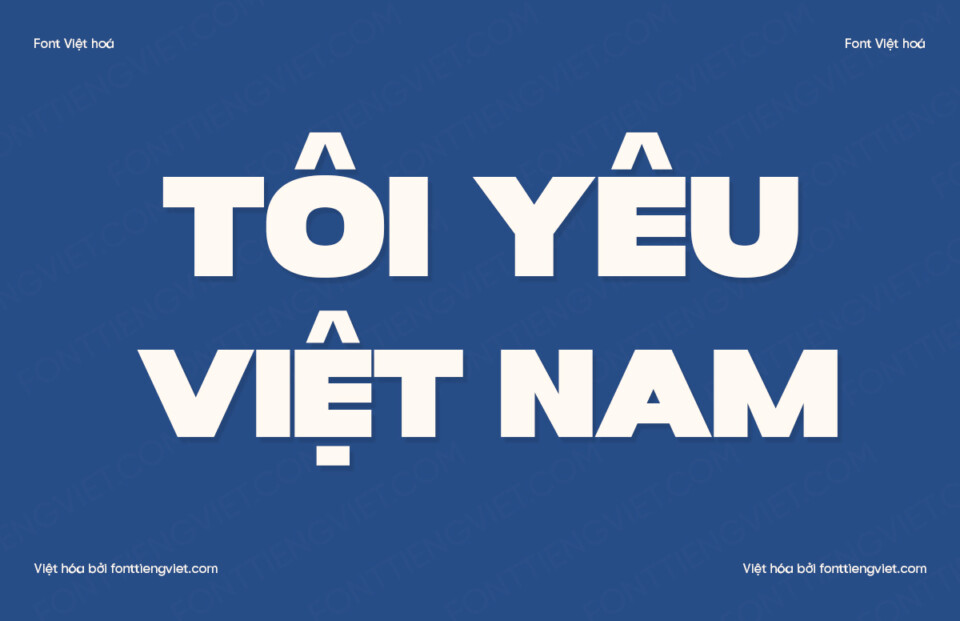
Font Việt hóa 1FTV VIP DINKO
Font Việt hóa 1FTV VIP DINKO – Font chữ cá tính cho thiết kế hiện đại
Nếu bạn đang tìm một font chữ vừa “chất”, vừa dễ dùng cho tiếng Việt, thì Font Việt hóa 1FTV VIP DINKO là lựa chọn rất đáng thử. DINKO nổi bật với đường nét mạnh mẽ, có độ “nghệ” vừa đủ để làm logo, tiêu đề, poster hoặc các ấn phẩm truyền thông. Đặc biệt, phiên bản Việt hóa giúp hiển thị đầy đủ dấu, hạn chế lỗi font khi dàn trang và in ấn.
1. Font Việt hóa 1FTV VIP DINKO là gì?
1FTV VIP DINKO là bộ font được Việt hóa tối ưu cho người dùng thiết kế tại Việt Nam. Nhờ hỗ trợ dấu tiếng Việt đầy đủ, bạn có thể sử dụng font cho nhiều mục đích mà không phải chỉnh sửa thủ công hay gặp tình trạng lỗi dấu. Đây là điểm cộng lớn khi bạn làm dự án branding, thiết kế social post, tiêu đề video hoặc landing page.
2. Ưu điểm nổi bật của font DINKO Việt hóa
Không chỉ đẹp, font DINKO còn được nhiều designer lựa chọn vì tính ứng dụng cao và khả năng tạo điểm nhấn mạnh. Dưới đây là những ưu điểm tiêu biểu:
• Việt hóa chuẩn: hỗ trợ đầy đủ ký tự tiếng Việt, dấu rõ, không bị vỡ chữ.
• Phong cách cá tính: phù hợp thiết kế logo, poster, bìa sách, banner quảng cáo.
• Dễ phối: kết hợp tốt với font sans/serif để tạo bố cục hài hòa.
• Tối ưu hiển thị: dùng tốt trên cả thiết kế số (digital) và in ấn.
3. Ứng dụng thực tế của Font Việt hóa 1FTV VIP DINKO
Với đặc trưng hiện đại pha chút retro, font DINKO thường được dùng trong các dự án cần tạo cá tính thương hiệu. Bạn có thể ứng dụng font cho:
• Thiết kế logo, tagline thương hiệu
• Thiết kế poster, banner, social media
• Tiêu đề thumbnail YouTube, TikTok
• Thiết kế bao bì, nhãn sản phẩm, menu
• Typography cho website/landing page
6. Lưu ý khi sử dụng font